Точки над «ё» в рукописном шрифте: как выбрать форму, высоту и интервал
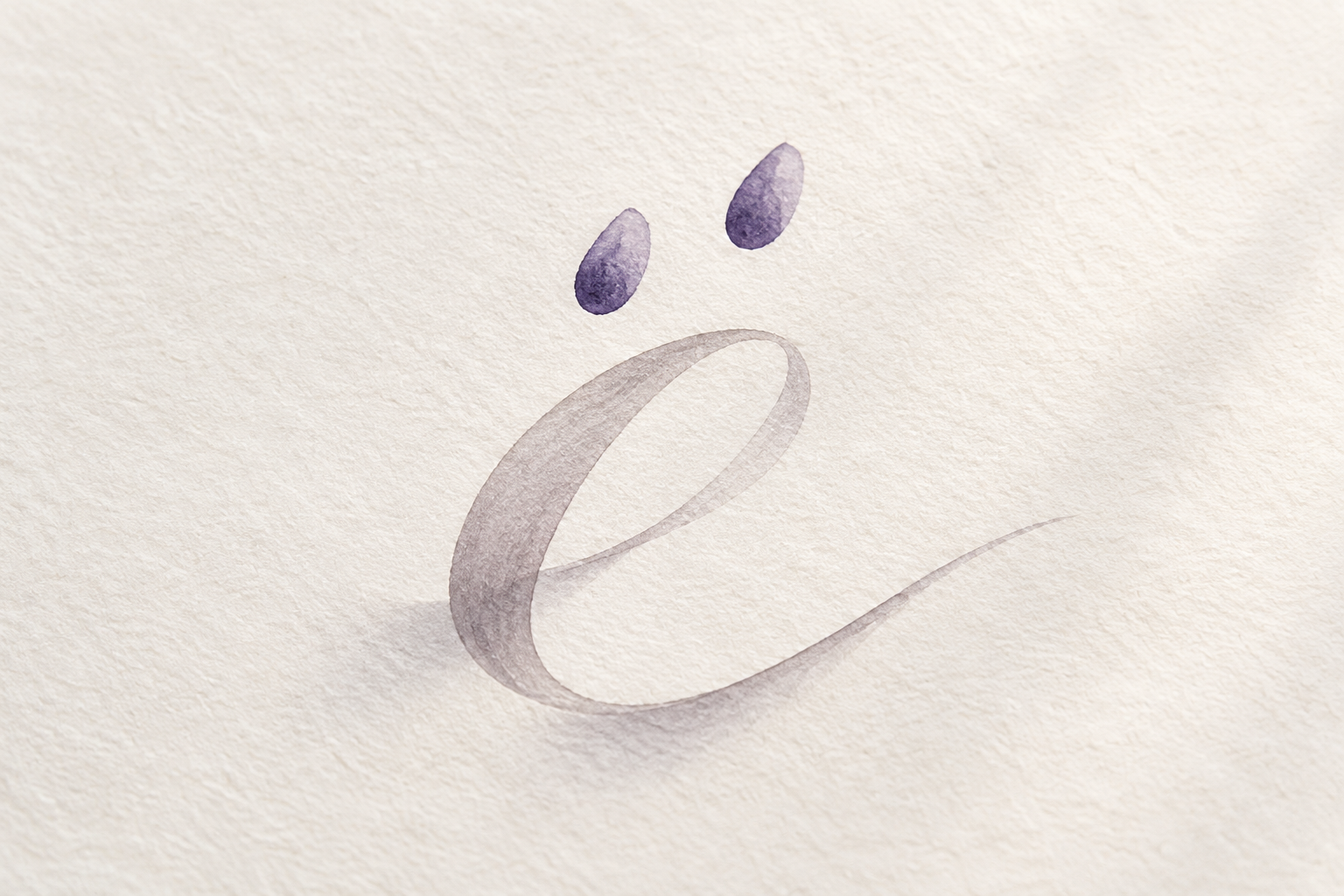
Две точки над «ё» — маленькая деталь, от которой зависит чтение целого слова. В рукописном шрифте важно согласовать их размер, наклон и расстояние между собой, а затем проверить высоту над буквой и просвет до строки сверху. Ниже — способ выбрать форму точек, настроить их для прописной и строчной буквы и проверить результат в реальном наборе.
Что именно нужно согласовать
«Ё» состоит из основной буквы и двух надстрочных элементов. В рисунке от руки точки часто воспринимаются как быстрые отдельные жесты; в шрифте же они повторяются в каждом слове и становятся частью системы. Они должны выглядеть родственными штрихам алфавита, оставаться различимыми в небольшом кегле и не сталкиваться с соседней строкой. Эти требования связаны: увеличить точки ради видимости недостаточно, если после этого они начинают выглядеть как случайный акцент или занимают слишком много места.
Начните с конкретного применения. Для коротких подписей с крупными буквами можно сохранить живой жест и заметный наклон. Для заметок, длинных текстов или мелкого экранного набора лучше сделать точки компактными и устойчивыми. Это не вопрос правильной традиции: задача — сохранить индивидуальный почерк и не вынуждать читателя угадывать слово.
Перед правкой запишите, где именно будет использоваться гарнитура: в заголовке, абзаце, подписи, карточке или сразу в нескольких местах. Это поможет выбрать правильный размер контрольного набора. Если шрифт предназначен сразу для разных условий, не пытайтесь вывести идеальную форму из одного примера крупной буквы: потребуется проверить её в нескольких масштабах.
Подберите форму точек по характеру штриха
Сначала посмотрите на повторяющиеся формы в готовых строчных буквах: округлые окончания, капли, короткие засечки, овальные контуры или прямые срезы. Точки над «ё» не обязаны буквально копировать окончание штриха, но должны принадлежать тому же визуальному языку. Если в буквах преобладают мягкие округлые завершения, резко квадратные точки могут казаться вставленными из другого шрифта. Если почерк угловатый и быстрый, идеально геометрические кружки могут, наоборот, выглядеть слишком стерильно.
Нарисуйте несколько вариантов рядом: круг, короткий овал, каплю, небольшую наклонную черту. Не выбирайте по отдельной крупной букве. Сравните каждый вариант с характерной дугой или окончанием штриха в вашем алфавите. Затем поставьте варианты над одной и той же основой «е» и уменьшите их до размера, который действительно будет встречаться. Так легче заметить, какие точки сохраняют характер, а какие превращаются в одинаковые пиксельные пятна.
Для первого сравнения полезно удержать неизменными ширину и место пары, меняя только очертания. Иначе трудно понять, какая именно правка улучшила знак. После выбора контура отдельно настройте толщину и наклон. Если точка в собственном размере выглядит выразительно, но при уменьшении исчезает, проверьте её вместе с буквами, а не добавляйте деталей, которые не переживут вывод.
Пара точек должна читаться как пара, а не как одна растянутая черта или декоративная россыпь. Сначала задайте каждой точке собственный контур и толщину, затем настройте промежуток между ними. Равенство размеров — полезная отправная точка, но не обязательный закон: наклон почерка и ширина верхней части «е» могут потребовать оптической коррекции. Оценивайте промежуток на глаз при реальном размере, а не только по числу единиц в редакторе.
Настройте высоту и положение над буквой
Отправной точкой служит верхняя часть строчной «е»: расположите точки над ней так, чтобы они воспринимались продолжением знака, но между нижним краем точки и основным контуром оставался ясный воздух. Если точки слишком прижаты, они сливаются с верхним штрихом при уменьшении или на плотной печати. Если отнести их чрезмерно высоко, буква распадается на два визуально независимых элемента и создаёт ненужную высоту строки.
Не ставьте точки механически по центру ширины буквы. Сравните общий силуэт «е» и пару точек: центр композиции должен быть устойчивым, даже если основной штрих асимметричен. В связном почерке точки могут слегка следовать направлению движения руки, но не обязаны продолжать соединительную линию. Их задача — быстро обозначить отличительный признак «ё», а не изображать движение пера любой ценой.
Чтобы найти рабочее положение, сделайте три пробных варианта с небольшим сдвигом всей пары: чуть влево, по центру, чуть вправо. Сравните их в одном слове и не рассматривайте по очереди на большом увеличении: рядом они воспринимаются честнее. Если один вариант кажется накренённым, проверьте не только координату пары, но и угол её точек. Нередко именно наклон создаёт впечатление, что диакритика съехала.
Проверьте отдельную строчную и прописную формы
У строчной и прописной «Ё» разные пропорции основы. Нельзя просто увеличить строчный знак целиком и считать задачу решённой: прописные буквы обычно имеют другую ширину и занимают иное место в строке. Сохраните родство точек — их форму, наклон и общий вес, — но проверьте, как пара соотносится с верхним контуром каждой основы. В паре «е/ё» и «Е/Ё» различительный признак должен быть заметен, но не обязательно иметь один и тот же абсолютный размер.
Итог: проверяйте пару в составе слова
Чтобы «ё» читалась уверенно, выберите точки в характере алфавита, настройте их по отношению к основе и проверьте свободное место над знаком. Затем сравните строчную и прописную версии, уменьшите пробу, проверьте абзац и готовый экспорт. Если вы создаёте собственный рукописный шрифт, перенесите букву в Fontgenerator вместе с остальными символами и оцените её уже в набранном тексте.